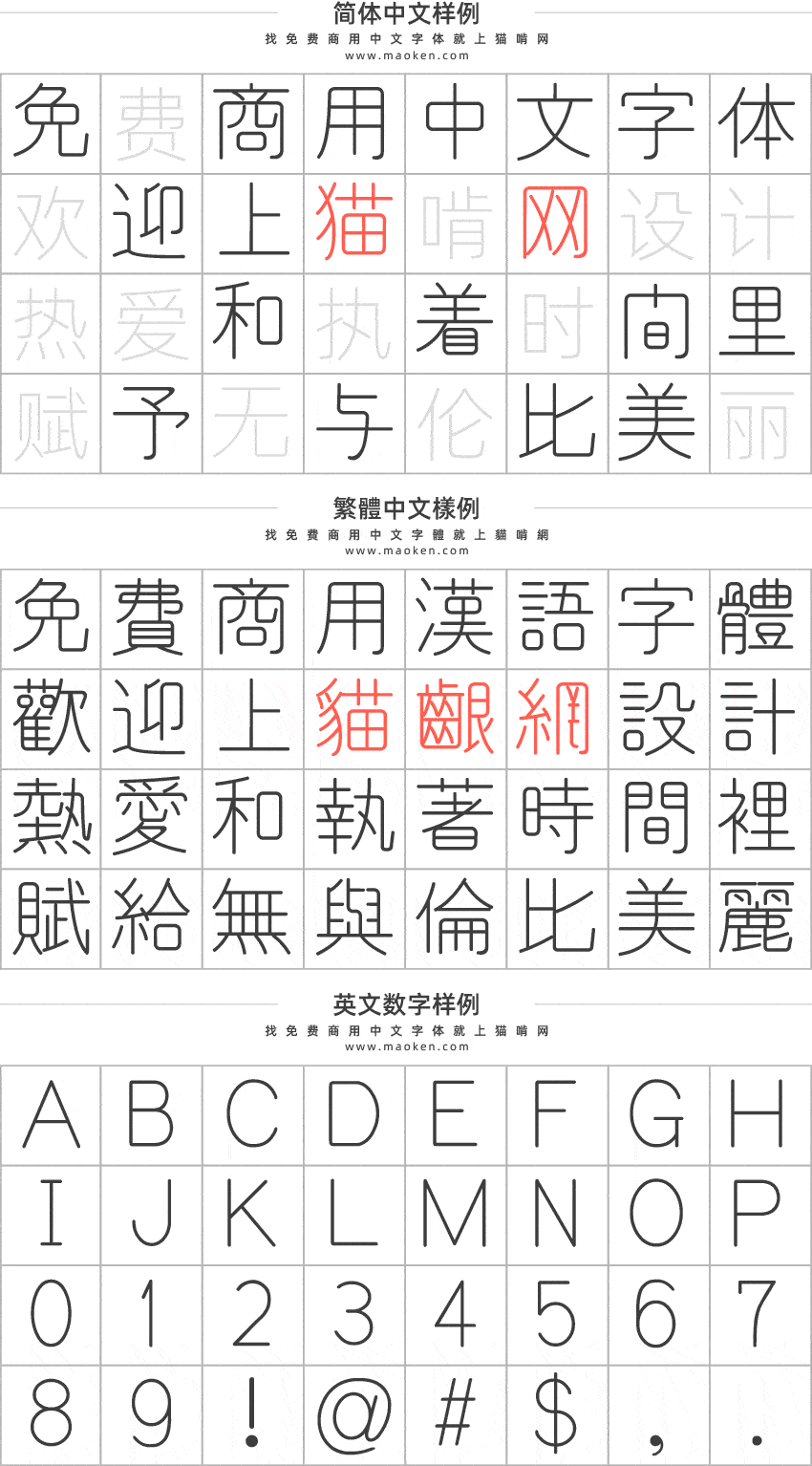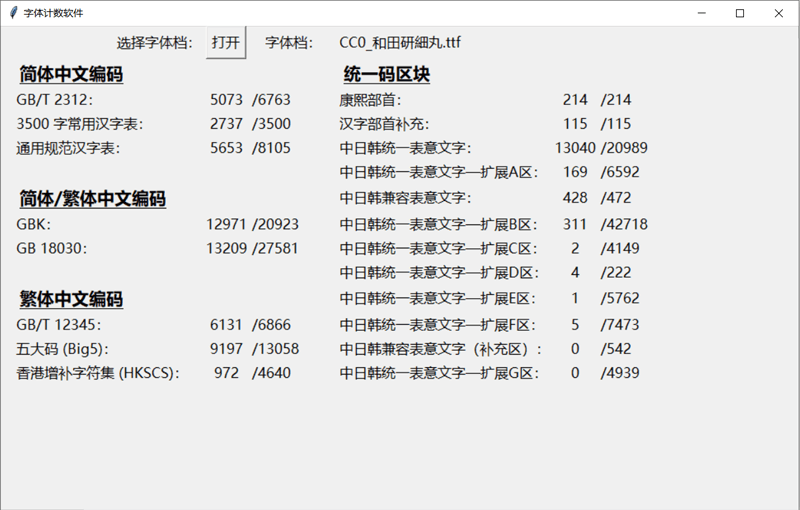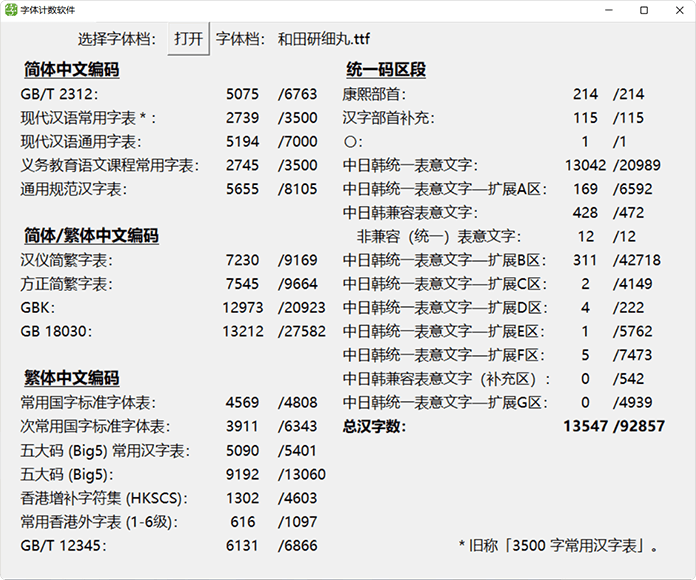
和田研字体:日系细圆体风格特色免费商用字体
和田研字体首次发布于2004年,是一款年代相对久远的字体,但是迄今为止依然在持续维护更新中。作者是和田研,以简单的元素来表达字体的美感且每一个字体的直角转折处都以椭圆角来做替代,整个字体的设计都充满了浓浓的古典风格。
在猫啃网下载的字体压缩包里面包含了两款字体,分别是“和田研细丸”和“和田研中丸”,细丸笔画较细,而中丸笔画较粗。而字体文件上带有P的,则是代表等宽字体。